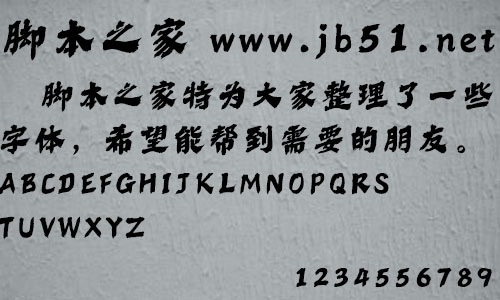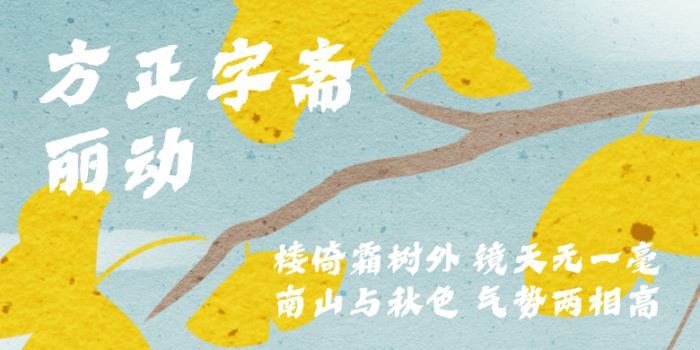
方正字齋麗動由方正字庫劉漢旭設計師出品的藝術(shù)字體,該字筆觸粗實,橫豎結(jié)宜,簡單排版綽綽有余,整體質(zhì)量基本穩(wěn)定,適合應用于藝術(shù)設計、平面宣傳設計、網(wǎng)頁設計,書法等領(lǐng)域。
如果說市面上的楷書飽和或太多了,那隸書相對少了很多,可選擇性也小,且給人橫平豎直的傳統(tǒng)印象。藝術(shù)大師達•芬奇說,預賦靜止以生命,必先使其有動感。就字的外形面貌而言,動感不是美術(shù)字體的專屬。動感隸書今天有的一見。為探索其可能性,賦予隸書以動感,而且一反常規(guī)的老態(tài)龍鐘印象,難度相當大。 《方正字齋麗動》是一款有動感隸書風格的字,與傳統(tǒng)相比,這款字青年有活力,給人積極的一面。字重偏粗,適合做標題,橫豎結(jié)宜,簡單排版綽綽有余,整體質(zhì)量基本穩(wěn)定。字體通過載體傳遞力量,需要我們不斷努力縱挖,嘗試更多可能性。